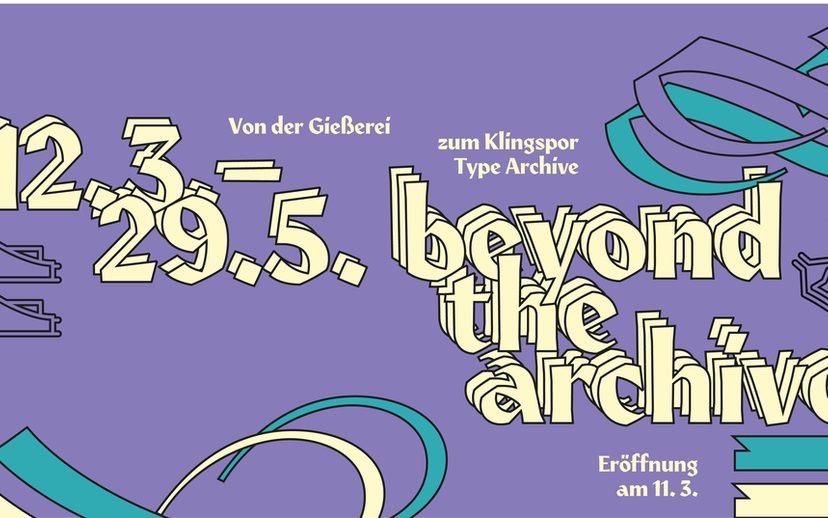
Beyond the Archive: von der Gießerei zum Klingspor Type Archive
In Offenbach war mit Gebr. Klingspor eine international bekannte Schriftgießerei ansässig, die mit ihrem künstlerischen Anspruch Maßstäbe setzte. Ihr Nachlass bildet heute einen der Kernbestände des Archivs im Museum. Die erhaltenen Objekte gewähren einen einmaligen Einblick in die Arbeitsprozesse der Schriftgestaltung im frühen 20. Jahrhundert.
Aber wie ist der Blick heute, 100 Jahre später, auf dieses Archiv und das darin lagernde Material? Wie kann es neu befragt werden? Und was können wir heute noch von ihm lernen?
Die Ausstellung entsteht in Zusammenarbeit mit dem Klingspor Institut für Schriftgestaltung und wird von HfG-Studierenden konzipiert und umgesetzt. Passend dazu wird zeitgleich das Klingspor Type Archive, eine digitale Archivplattform, entwickelt.